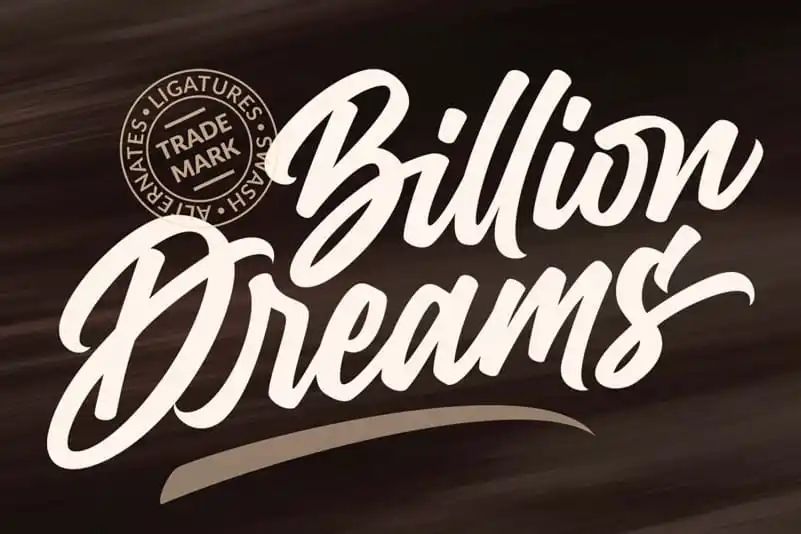
Billion Dreams Script Font – Download Grátis
Billion Dreams Script Font é uma opção irresistível para designers em busca de uma tipografia script que traga vida e personalidade a seus projetos criativos. Especialmente indicada para logotipos, esta fonte possui traços afiados da caligrafia que dão um toque único e distintivo às linhas gráficas. Seu design inovador inclui alternativas estilizadas, letras flutuantes e ligaturas, garantindo uma grande variedade de opções sem repetitividade desnecessária. Um dos atributos mais apreciados é seu suporte lingüístico extenso, cobrindo todos os escritos latinos europeus. Esta fonte abrange todas as letras necessárias para qualquer projeto gráfico e ainda inclui símbolos de pontuação e números, tornando-a uma escolha ideal para projetos multifacetados. Para designers em busca de um giro mais elaborado na tipografia, Billion Dreams Script é perfeito. Seu estilo único é capaz de adicionar um toque sofisticado a qualquer projeto, tornando sua fonte uma opção indispensável em seu arsenal criativo. Sua qualidade e variedade oferecem uma ferramenta versátil para criar design gráfico que seja tanto incrivelmente original quanto profissional.